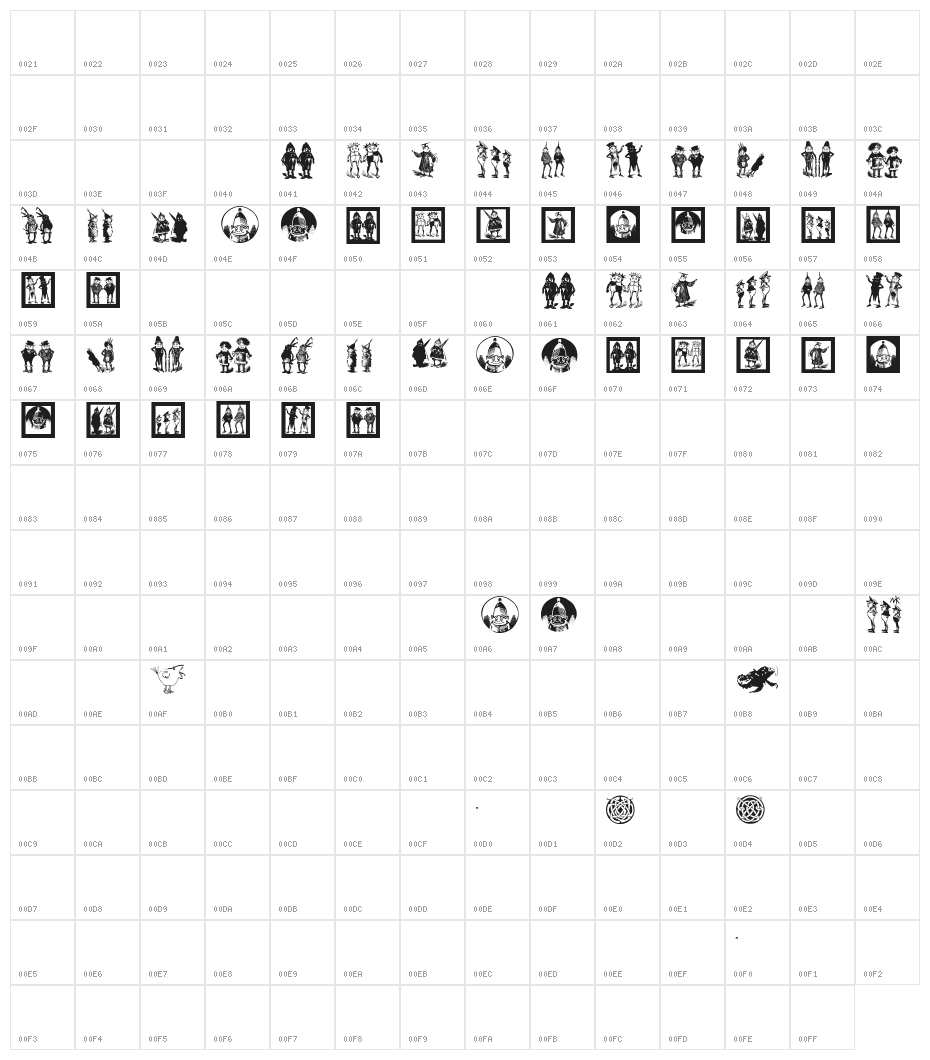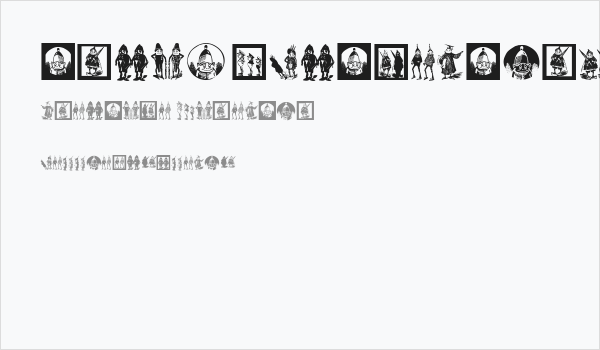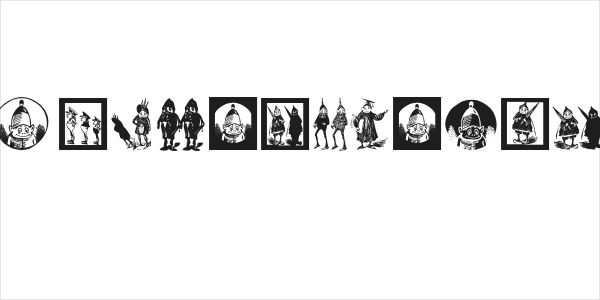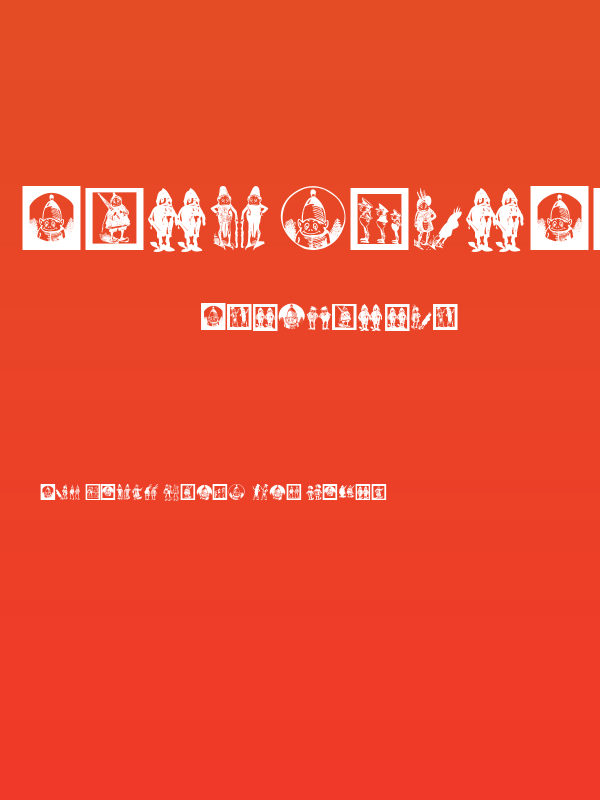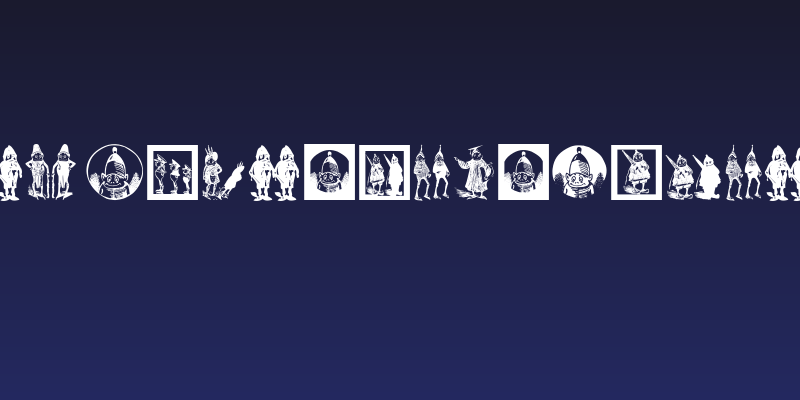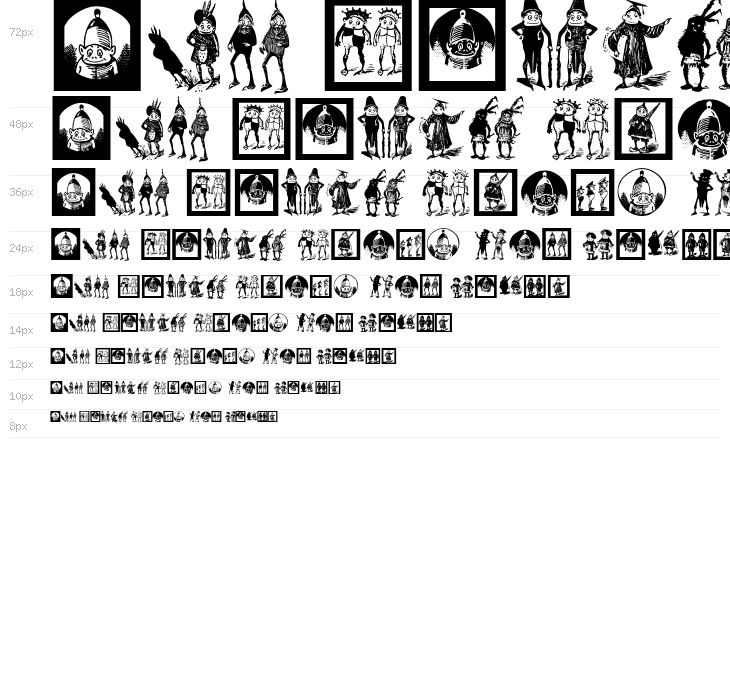
TrainWhatVectorMeans Font
| Gesamtstil | Decorative, Whimsical, Playful |
| Anwendungsfall | Headlines, Logos, Posters, Themed Graphics |
| Vorgeschlagene Projekte | Children's books, storybook titles, posters, themed party invitations, creative branding, and playful packaging. |